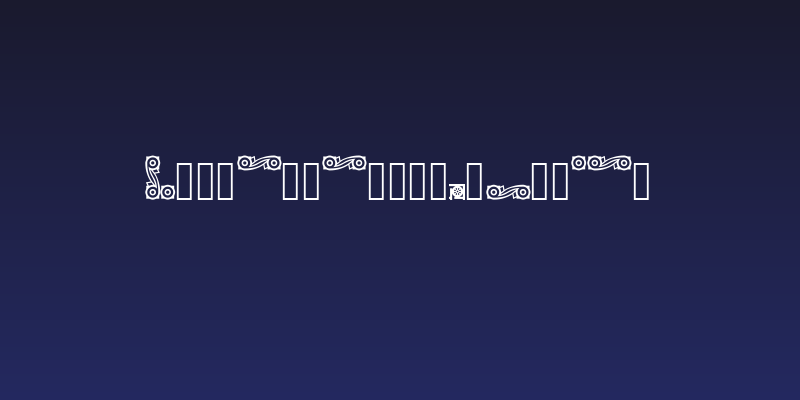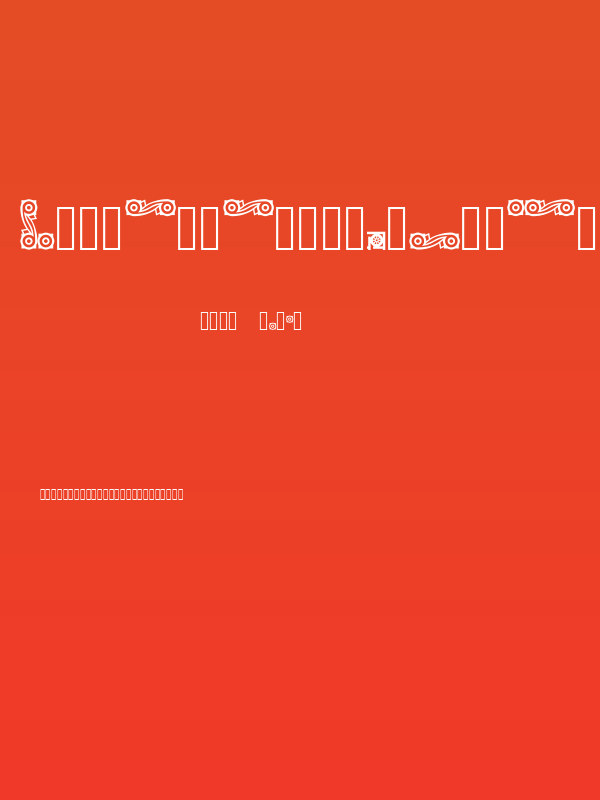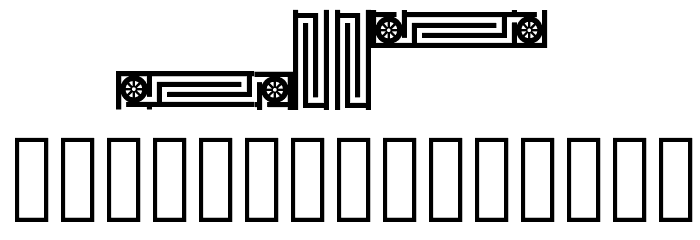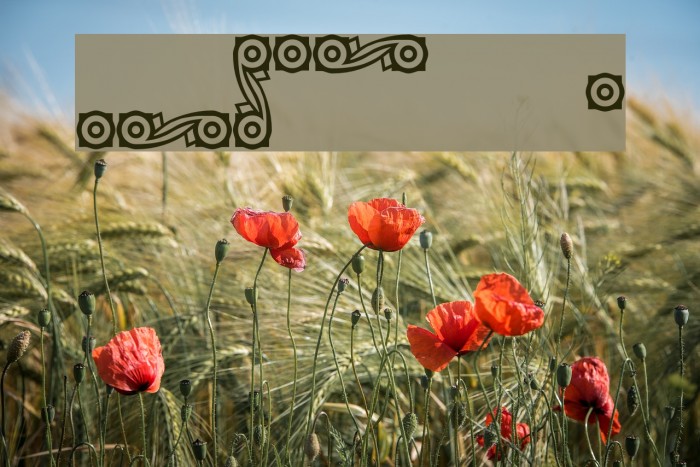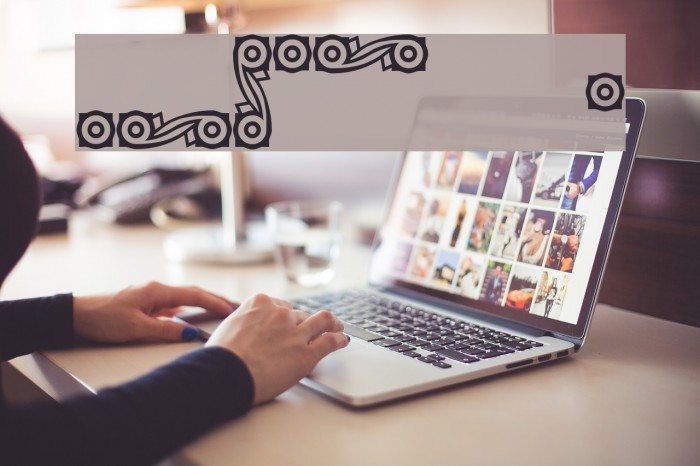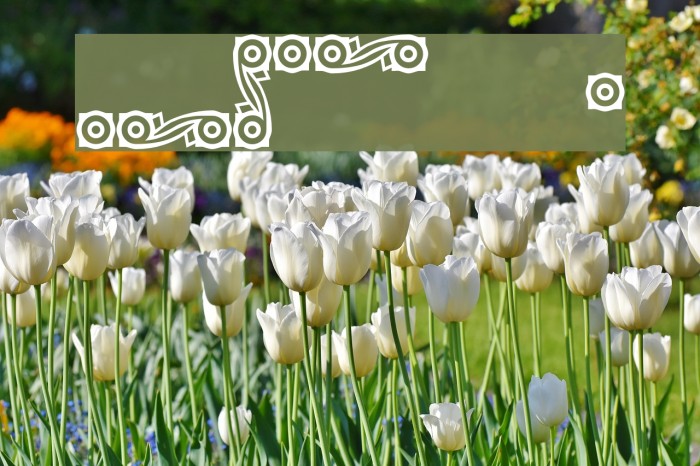
CastlePressNo2 border Font
| समग्र शैली | Vintage |
| उपयोग का मामला | Headlines, Artistic projects, Themed designs |
| सुझाए गए प्रोजेक्ट | Ideal for use in themed invitations, historical event posters, or artistic projects requiring a vintage touch. |